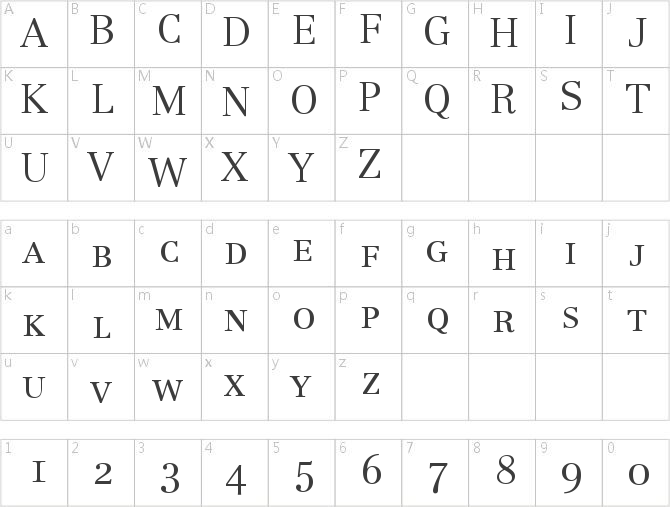
字体名称: Century
Century Reprise LightOldStyle S
Century Reprise LightOldStyle S字体字库是一款让人赏心悦目、百看不厌的英文字体,适合各类广告和产品包装设计应用,字体大小0.05MB,格式为ttf字体,上传用户是快乐围棋,作者/版权方为未知